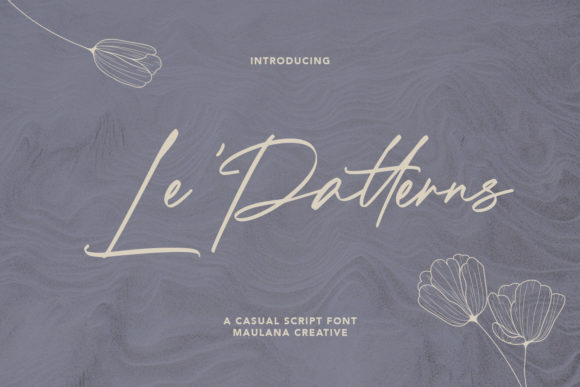
Le Patterns - это стильный и четкий шрифт скрипта.
Он имеет стильный, элегантный и современный вид, который может быть использован для логотипов, брендинга, приглашений, канцелярских принадлежностей, свадебных конструкций, сообщений в социальных сетях, и многое другое!